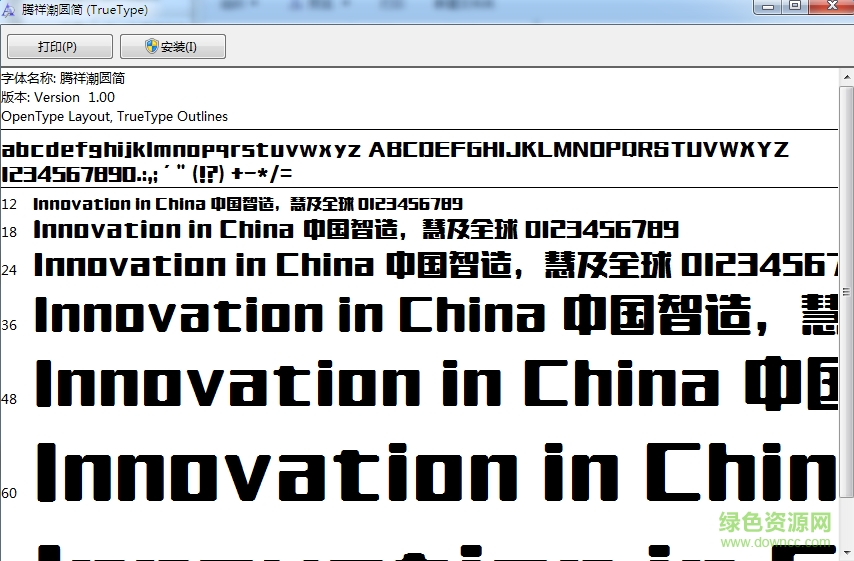
騰祥潮圓簡(jiǎn)是一款非常美觀的電腦字體,字形結(jié)構(gòu)扁方、端莊,橫豎筆畫(huà)粗細(xì)比例適度、豎筆粗壯有力,布白均勻、行文貫通,可用于印刷出版、包裝設(shè)計(jì)、廣告設(shè)計(jì)、網(wǎng)頁(yè)設(shè)計(jì)等領(lǐng)域,喜歡可以來(lái)綠色資源網(wǎng)下載!
騰祥潮圓簡(jiǎn)是一款富于變化的美術(shù)類黑體,是在潮黑的基礎(chǔ)上變換設(shè)計(jì)而成。雖然字形結(jié)構(gòu)與潮黑相同,但兩款字的風(fēng)格氣質(zhì)截然不同。潮圓將潮黑的棱角柔化形成被融化之感,融化了的筆畫(huà)圓潤(rùn)富于親和力。